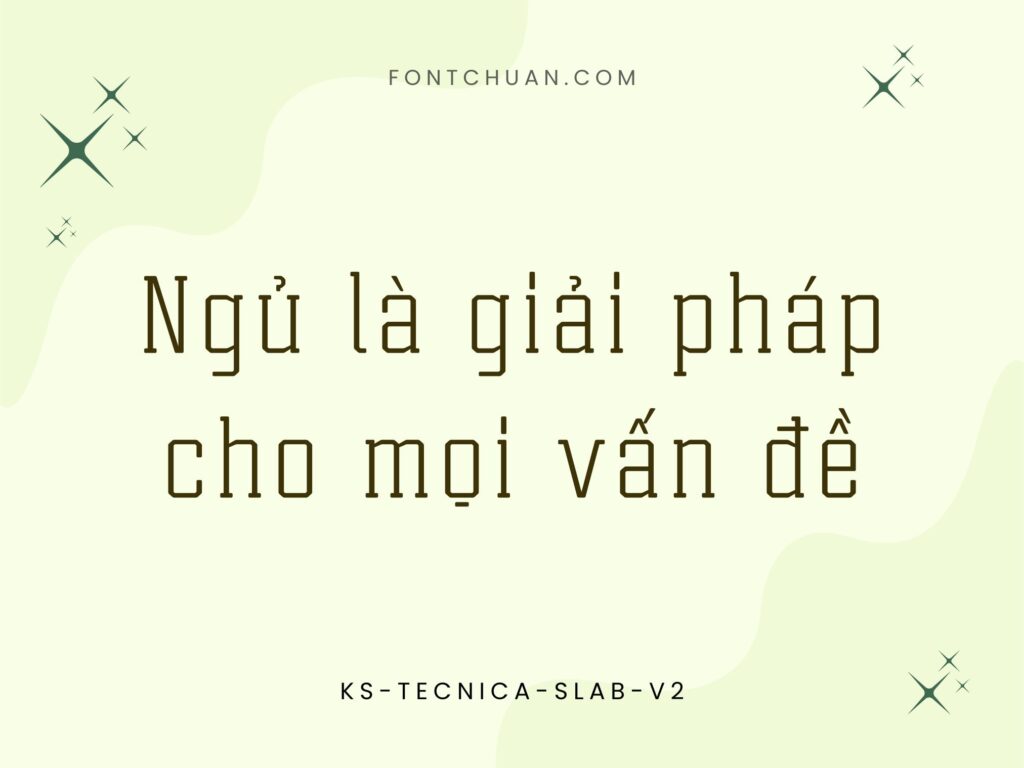
Font Ks Tecnica Slab V2 Việt Hóa
Tecnica Slab là một Font Slab Serif được thiết kế bởi Pablo Balcells và phát hành bởi Graviton vào năm 2014. Phiên bản Tecnica Slab V2 đã được Việt hóa bởi KS Font, hỗ trợ đầy đủ các ký tự tiếng Việt, mang lại trải nghiệm gõ chữ trọn vẹn cho người dùng Việt Nam. Ngoài tiếng Việt, phông chữ này còn hỗ trợ nhiều ngôn ngữ khác, mở rộng khả năng ứng dụng trong các dự án quốc tế. Việc Việt hóa được thành viên của Font Chuẩn chọn lọc và sưu tầm, nhằm đáp ứng nhu cầu bạn đọc và ứng dụng thực tế vào các dự án thiết kế. Bên cạnh đó, nhờ sự rõ ràng và dễ đọc, Tecnica Slab có thể kết hợp linh hoạt với các Font Monospace trong tài liệu kỹ thuật hoặc thiết kế mang tính hệ thống, giúp tăng tính chuyên nghiệp và cân bằng thị giác.
Về đặc điểm thiết kế, Tecnica Slab có cấu trúc chữ hình học với các chân chữ vuông vức, tạo cảm giác mạnh mẽ và hiện đại. Độ tương phản thấp và độ dày đồng đều giúp phông chữ trở nên dễ đọc ở các kích thước khác nhau. Các ligature được thiết kế tinh tế, tạo sự liền mạch và thẩm mỹ cao cho văn bản. Với những đặc điểm trên, Tecnica Slab phù hợp cho các ứng dụng như thiết kế logo, tiêu đề, bao bì sản phẩm và các dự án sáng tạo khác. Phông chữ này cũng thích hợp cho các thiết kế cần sự mạnh mẽ và hiện đại, như áp phích quảng cáo, tạp chí và các sản phẩm thương hiệu. Về ngành nghề, Tecnica Slab đặc biệt phù hợp với lĩnh vực quảng cáo, công nghệ, giáo dục và các ngành nghề cần sự sáng tạo và hiện đại trong thiết kế. Sự linh hoạt và tinh tế của phông chữ giúp nó dễ dàng hòa nhập vào nhiều phong cách thiết kế khác nhau, từ cổ điển đến hiện đại.
Bên cạnh các ứng dụng mạnh mẽ và hiện đại, Tecnica Slab cũng có thể được sử dụng như một Font valentine để thiết kế các sản phẩm lãng mạn, tinh tế như thiệp Valentine, banner hay poster dịp lễ tình nhân. Với cấu trúc chữ hình học vuông vức nhưng vẫn cân đối và dễ đọc, font này giúp các thiết kế vừa giữ được sự hiện đại, vừa tạo cảm giác ấm áp, ngọt ngào, phù hợp cho các dự án sáng tạo về tình yêu và các dịp đặc biệt.